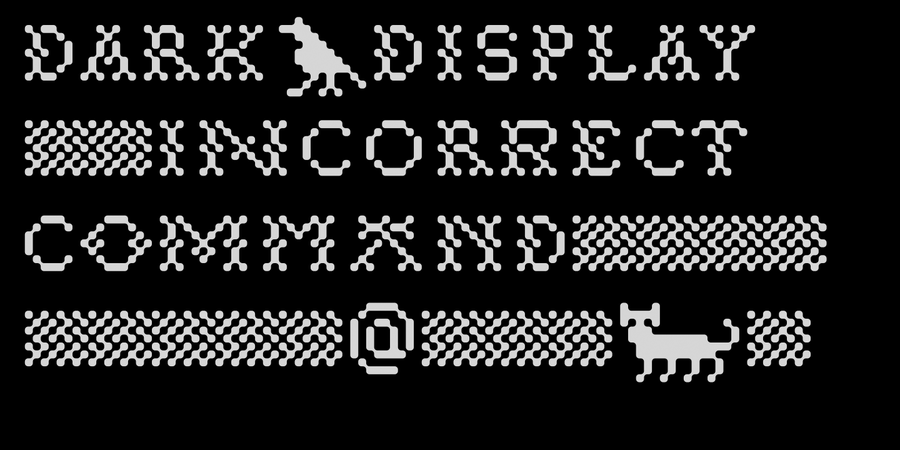
Digital Stitch – це вишивка цифрової ери. Цей шрифт є сумішшю піксельної графіки, традиційної вишивки хрестиком і друкованих плат. Підтримує багато мов і містить орнаменти і малюнки. Шрифт розроблений Лук'яном Турецьким в 2013 році.
оригінальний, характерний, дивний, загадковий, комп'ютерний, грайливий, потішний, незвичайний, експериментальний, прикольний, жахливий, страшний, містичний, таємничий, дробный, молодіжний, інопланетний, кислотний, екзотичний, психоделічний